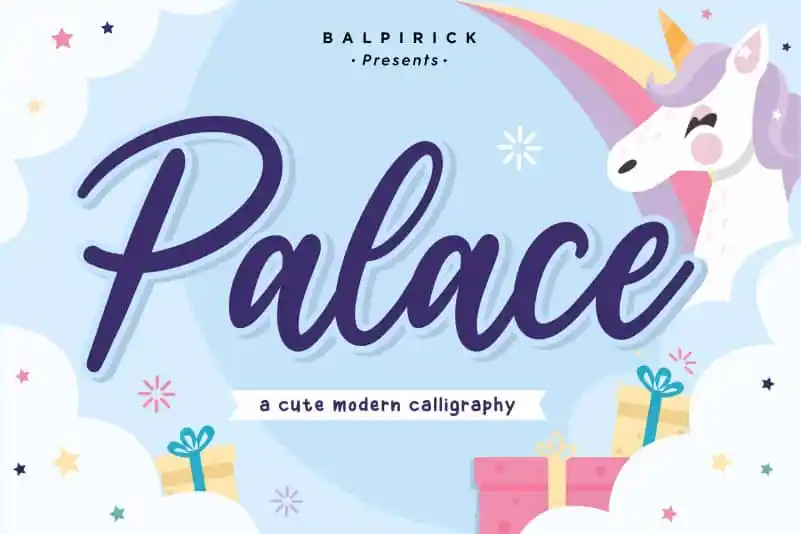
Palace Cute Calligraphy Font
A Palace Cute Calligraphy Font é a escolha perfeita para adicionar um toque autêntico e charmoso às suas criações digitais, seja no design de embalagens, marca, revistas ou redes sociais. Seja você uma pequena empresa buscando destacar-se em seu nicho ou alguém que deseja criar conteúdo especial para aniversários e casamentos, essa fonte oferece a oportunidade de expressar sua personalidade através das palavras num estilo elegante e encantador. Seja ela usada em títulos altos para destacar mensagens importantes no meio de um fundo mais neutro ou mesmo decorando textos cotidianos com delicadeza, essa fonte permite que você faça seu design soar sofisticado. Além disso, é perfeita para o uso em projetos relacionados à arte digital e design gráfico. Com Palace Cute Calligraphy Font, cada palavra escolhida ganha vida graças ao traçado elegante e ao charme único da fonte. Não importa se você está criando um produto ou serviço, uma publicação online ou até mesmo desenhando uma assinatura para seu blog pessoal, a Palace Cute Calligraphy Font oferece opções que irão tornar sua marca mais impactante. Essa é uma escolha inteligente para qualquer designer gráfico que busca dar vida aos textos de suas criações com estilo e elegância.